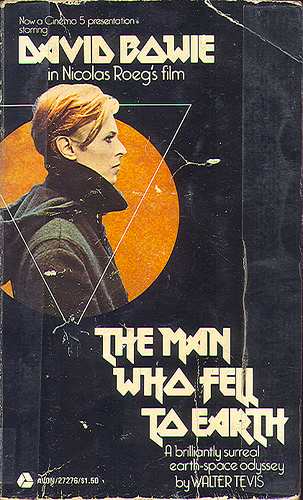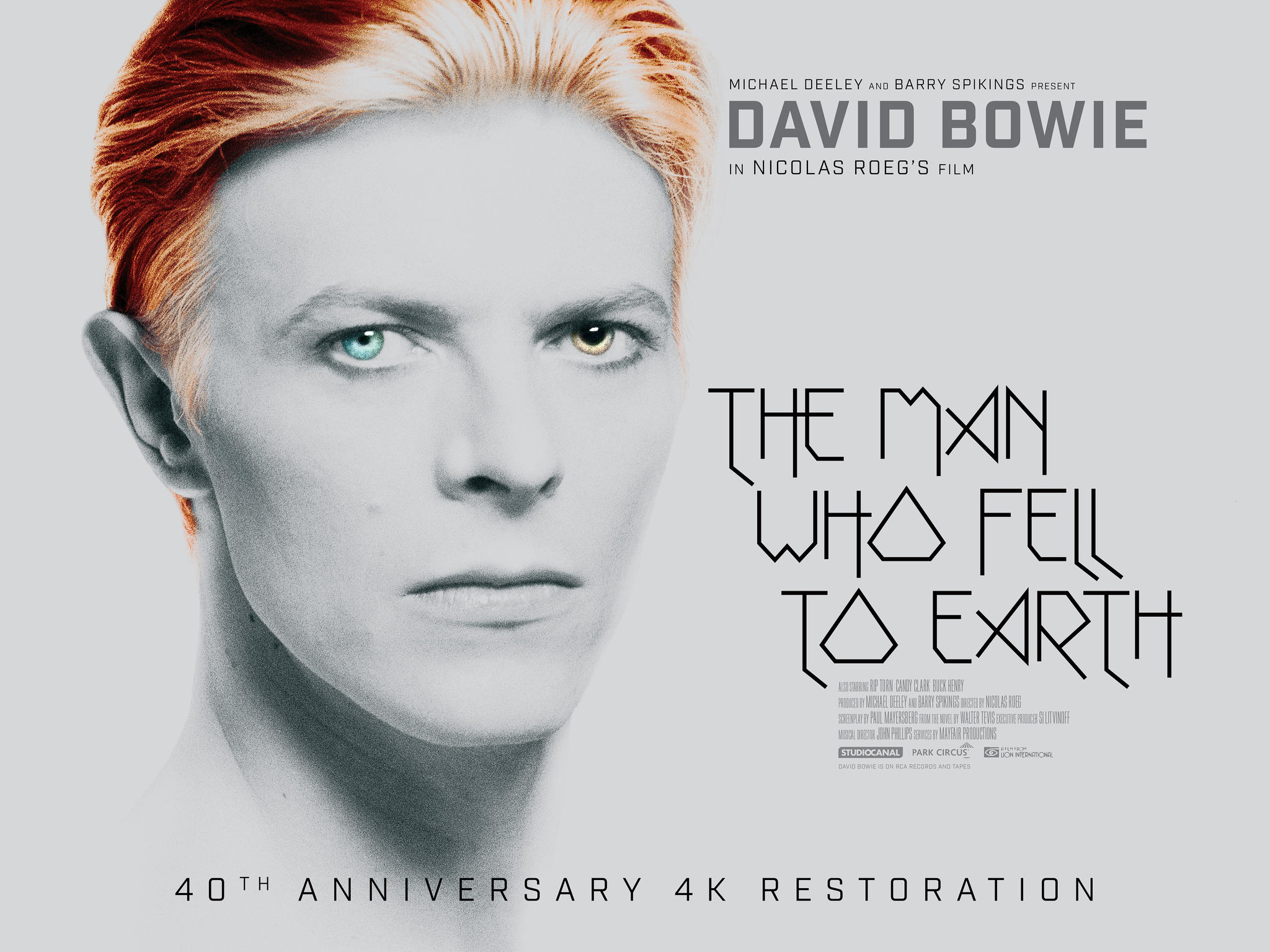
Gesucht (Der Mann der vom Himmel fiel)
ich such mal wieder was, oder was ähnliches. Hammergeile Schrift von einem David Bowie Cover.
Gibt es da was im Freebereich?? Wäre klasse, denn ich finde so jetzt nicht annahernd was passt.
In fett: http://typodermicfonts.com/metal-lord/
"Iron Maiden" ist sicher ein gutes Stichwort für diese Fonts …
Das Original sah übrigens so aus:
Muss ich nur schaun, wie ich die in dünn bekomme, denn das finde ich gerade superedel.
Selber konstruieren, wenn du nur die paar Buchstaben brauchst. Wurde beim Filmplakat auch so gemacht, siehe die beiden L.